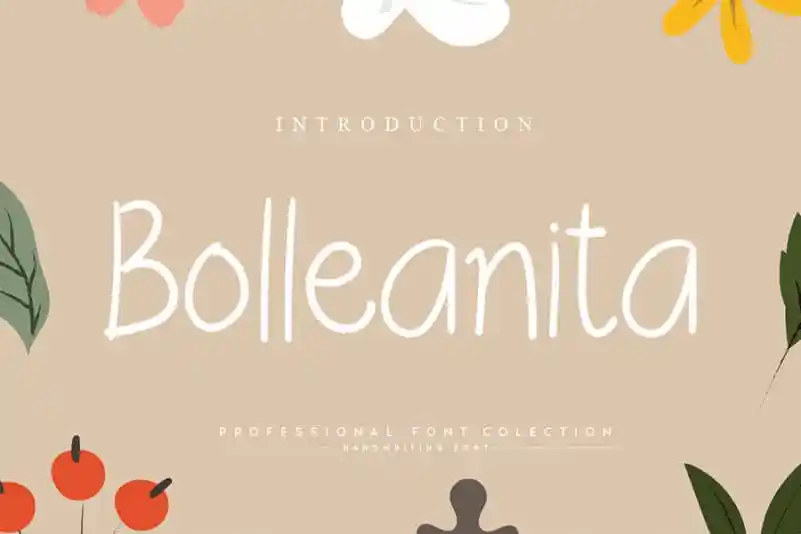
A Bolleanita Handwritten Font é uma elegante escolha para qualquer designer que busca adicionar uma pitada de originalidade às suas criações digitais. Esta fonte feita à mão captura a essência do estilo handwritten, combinando elementos refinados com uma escrita autêntica e confiável. Ideal tanto para trabalhos pessoais quanto profissionais, ela adicionará um toque único ao seu design sem comprometer a legibilidade necessária. Criada por andikastudio, a Bolleanita oferece uma variedade de opções que vão do simples texto a detalhes elaborados, tornando-a uma fonte versátil. Seja para criar anúncios persuasivos ou artigos de design fascinantes, esta fonte é perfeita para quem busca personalidade em suas criações digitais. Experimente agora e descubra o poder da Bolleanita Handwritten Font para fazer seu trabalho realmente destacar.